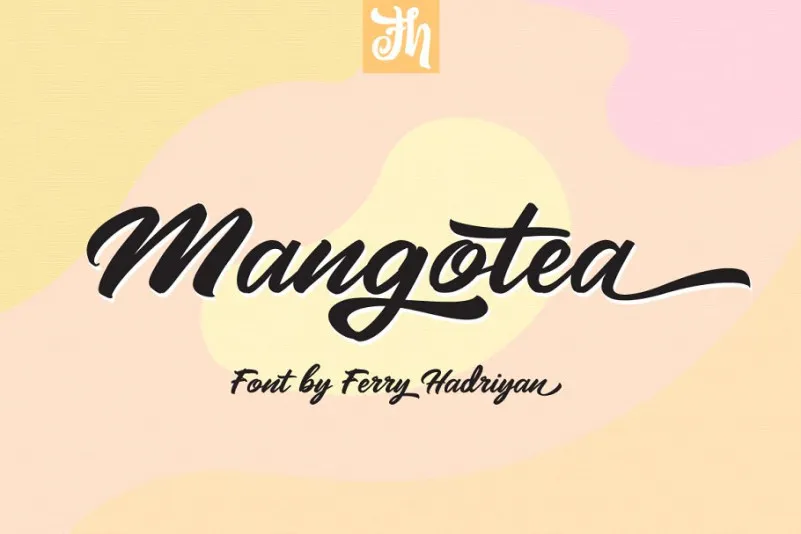
Mangotea Script Font – Download Grátis
A Mangotea Script Font é uma bela escolha para quem procura uma fonte script que seja agradável aos olhos e ideal para diversas aplicações, desde o design do seu blog até o desenvolvimento de materiais promocionais. Este estilo brush script foi projetado por FHFont com um toque delicado e sofisticado que faz dele uma opção perfeita para qualquer projeto visual, seja ele relacionado à wedding planning, eventos especiais, logotipos ou até mesmo a criação de adesivos personalizados. Com o recurso OpenType integrado, oferece uma variedade incrível de estilos e detalhes que torna sua fonte um elemento indispensável em qualquer projeto gráfico. A Mangotea Script é mais do que apenas uma fonte; ela é um acréscimo elegante e criativo ao seu design.